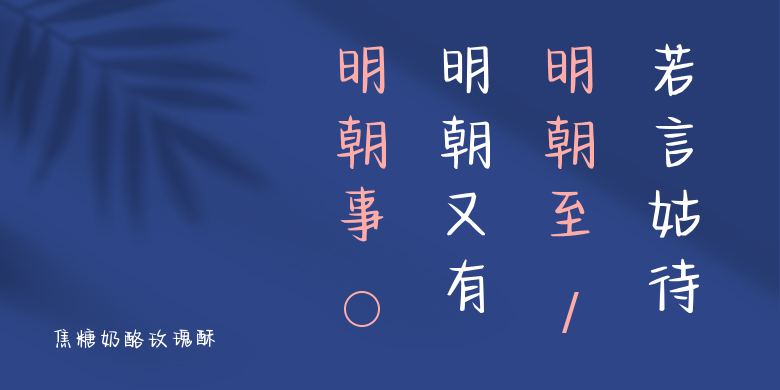
焦糖奶酪玫瑰酥
焦糖奶酪玫瑰酥,这款字体结构工整、笔画清晰,兼顾美观与易读性,适用于标题、正文、海报、包装、LOGO 等多种场景。字形优雅稳定,风格百搭耐看,适配日常排版与创意设计,让文字呈现更舒适、更具质感。焦糖奶酪玫瑰酥一笔一画,皆是细节,以均衡的比例、流畅的线条打造舒适视觉体验,字形端正大气,风格简约现代。无论是商业设计、品牌宣传还是日常排版,都能轻松驾驭,让文字更有格调与力量。焦糖奶酪玫瑰酥字体下载。